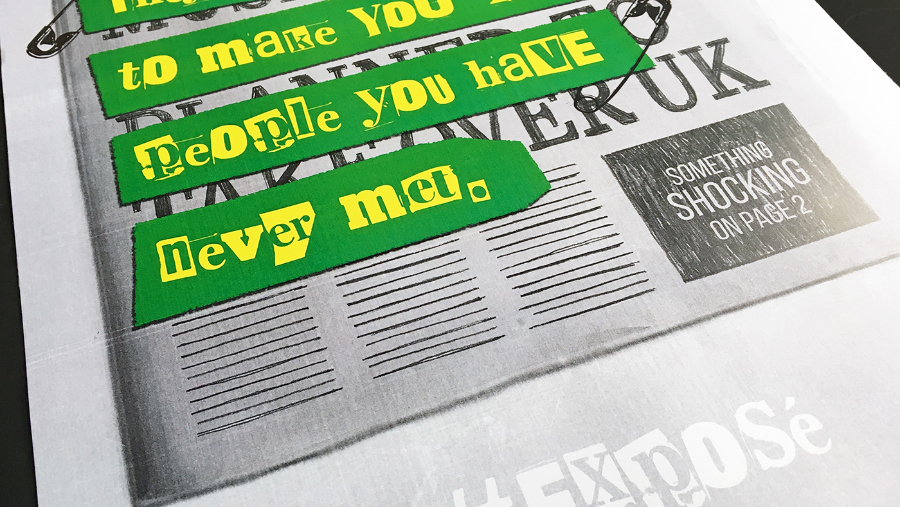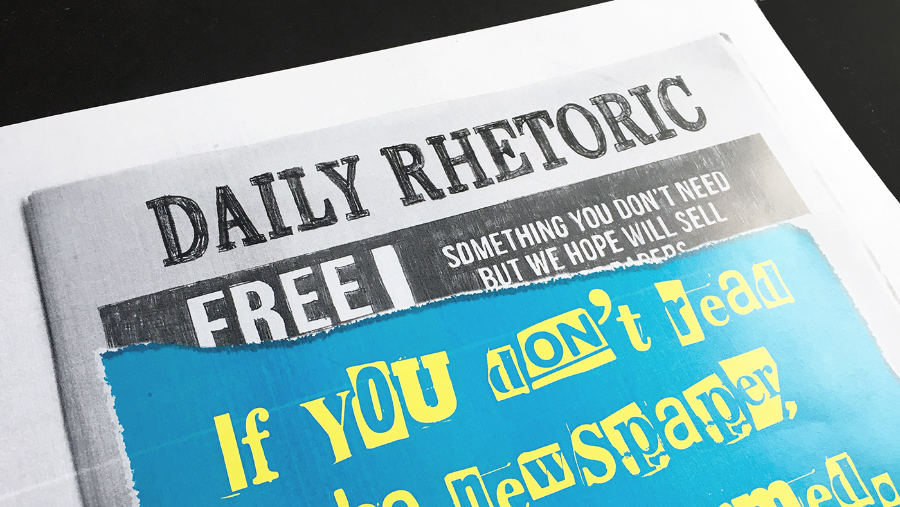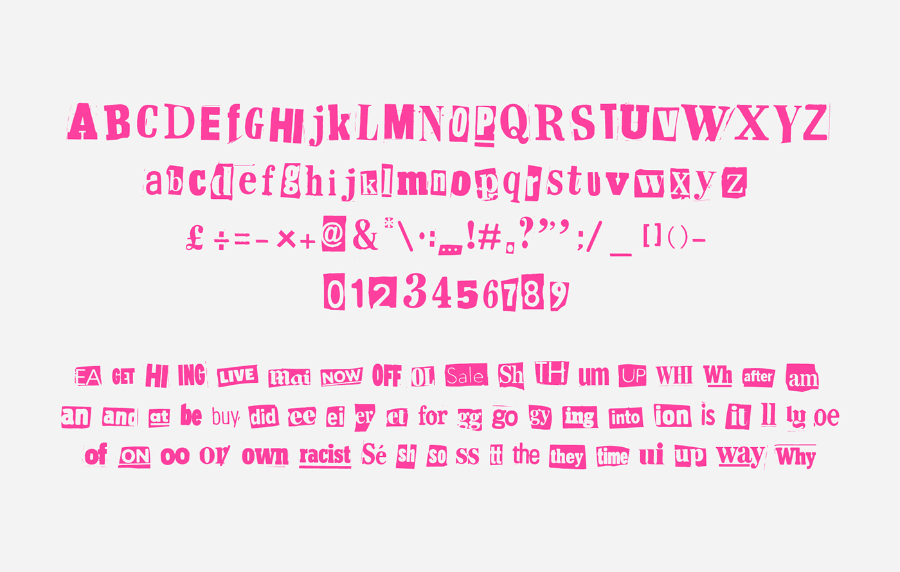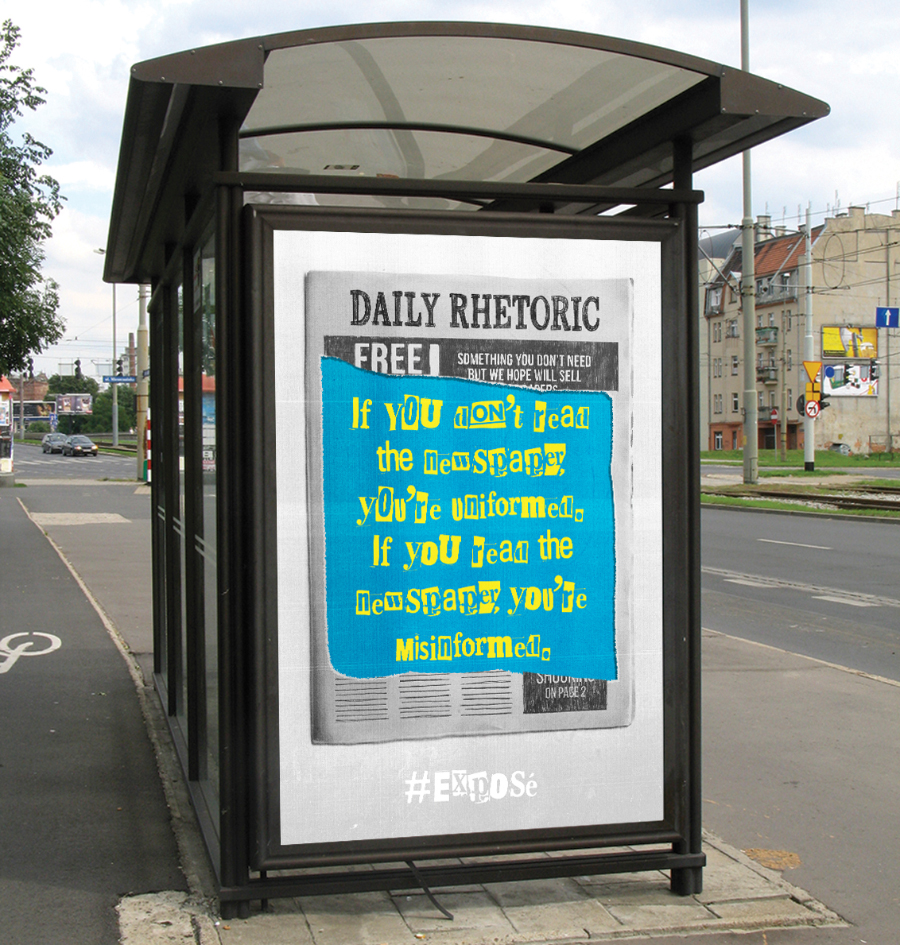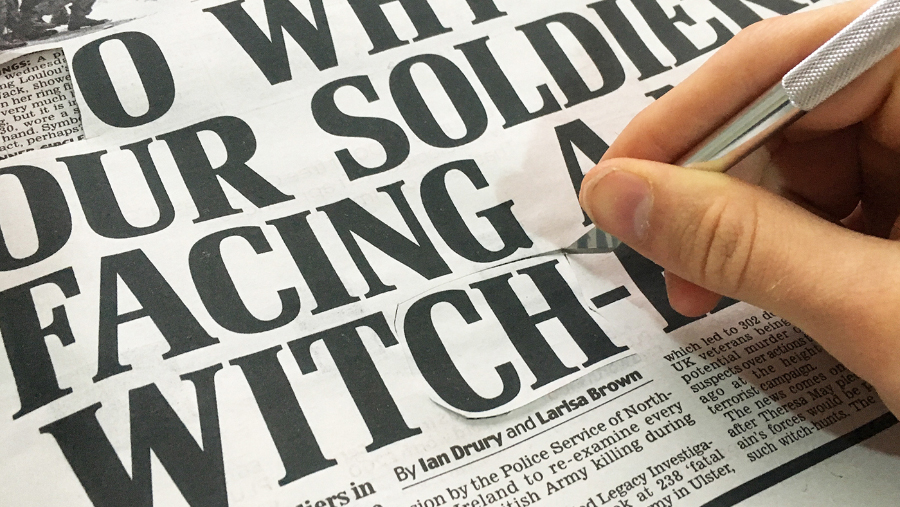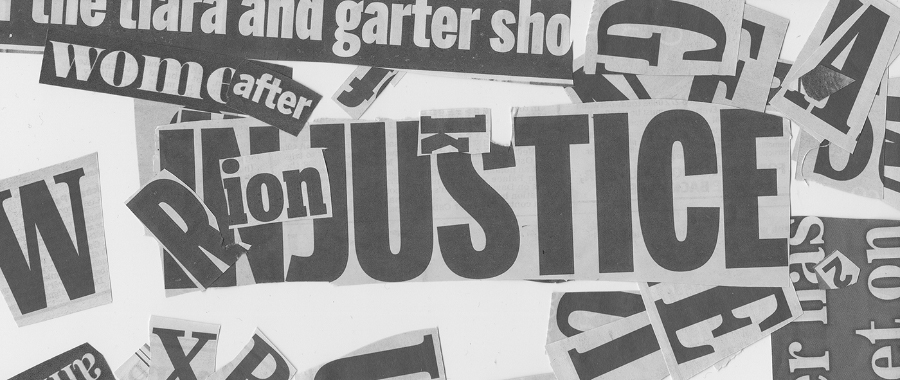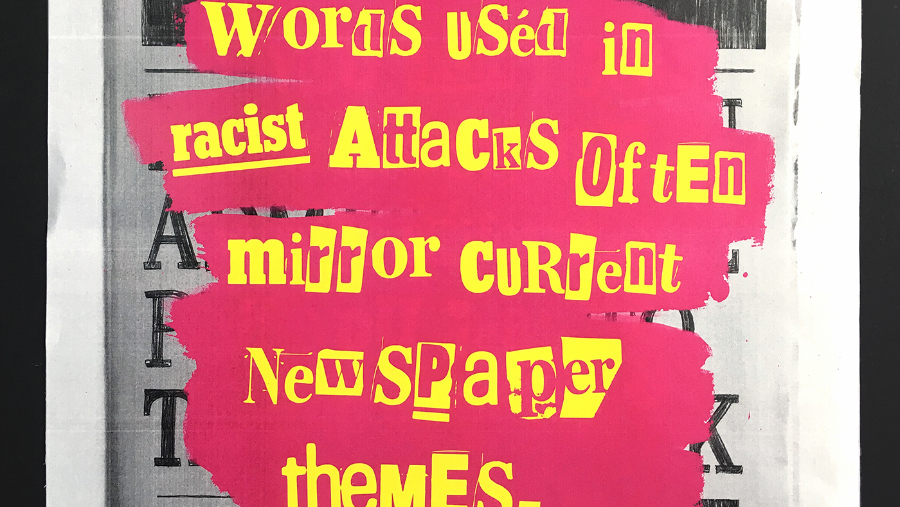
Exposé免费显示字体
Exposé免费显示字体是由詹姆斯刘易斯概念驱动的字体。提高人们对现代“新闻”中过度使用修辞的认识及其对人们的影响。来自剪报和重新使用报纸头条的字体。所有这些都是为了利用报纸对他们的憎恨言论,揭露他们如何操纵人。此外,字体还带有一个完整的英文字符集。还有50个连字可以自由地激发你和其他创意的头脑。因此,Exposé在这里传播信息,对当前的社会环境有自己的发言权,所以我们可以一起做出积极的改变。